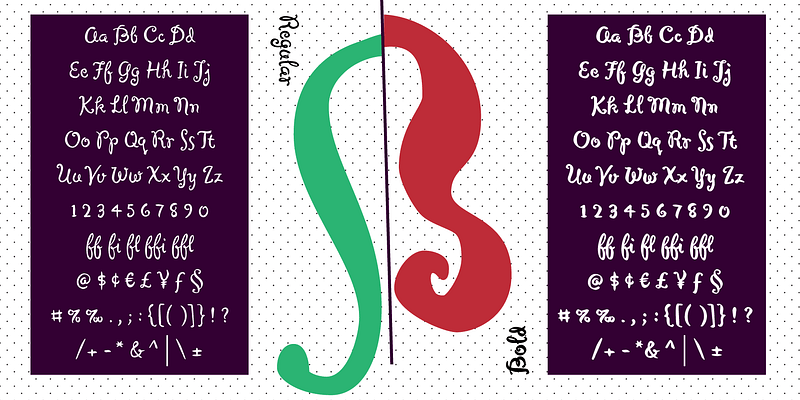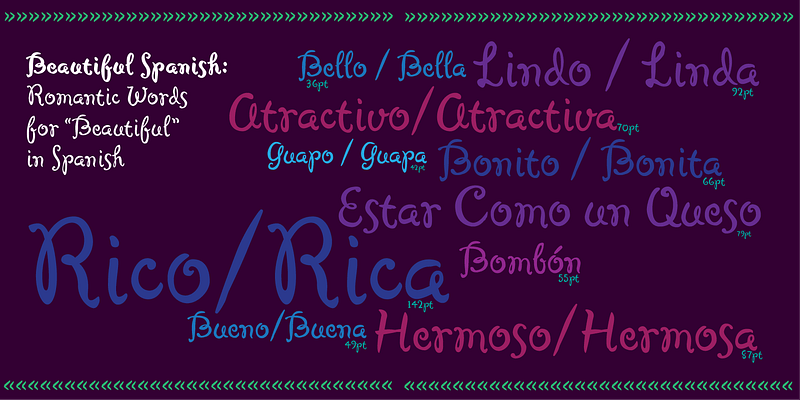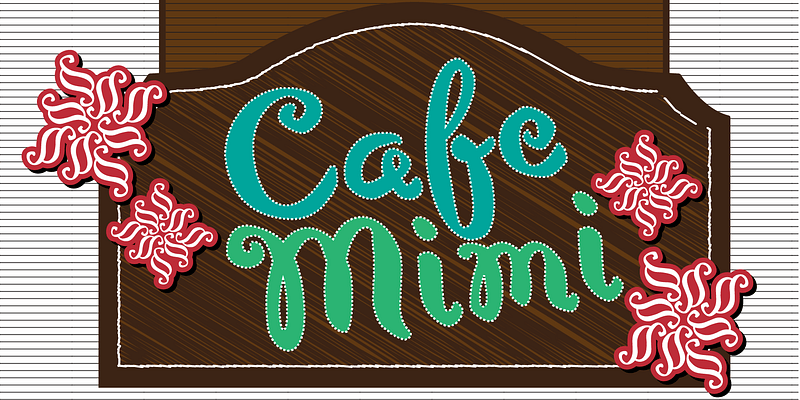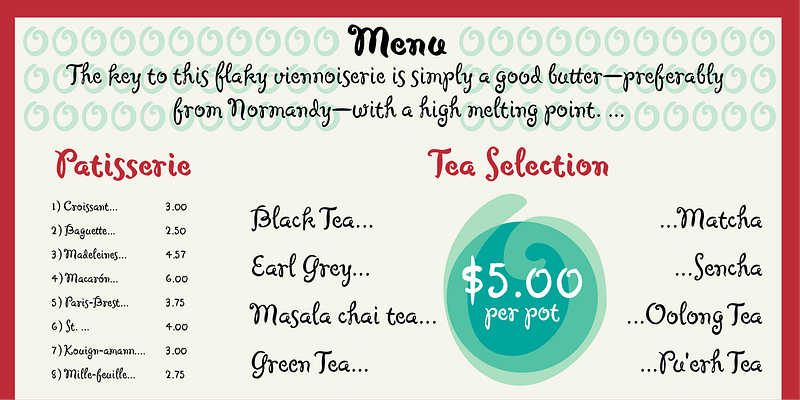
MVB Cafe Mimi를 디자인할 때 Kanna Aoki는 여러 주요 제조사의 패브릭과 접시를 디자인하고 있었습니다. Aoki가 카푸치노 컵 세트를 장식하기 위해 그린 몇 개의 단어에서 디자인을 따왔습니다. Aoki는 브러시를 사용하여 MVB 글꼴을 위한 Regular 두께를 만들었고, Bold는 디지털화 후 적용되었습니다. 여러 개의 이중 문자 합자를 사용하여 원래 손으로 그린 글자처럼 자연스럽고 즉흥적인 분위기를 느낄 수 있습니다. 소용돌이 모양과 자유롭게 흐르는 형태에도 불구하고 균형 있고 읽기 쉬운 스크립트로 유지하기 위해 세심한 주의를 기울였습니다. 기준선 위에서 깡충깡충 뛰면서도 발을 헛디디지는 않습니다.